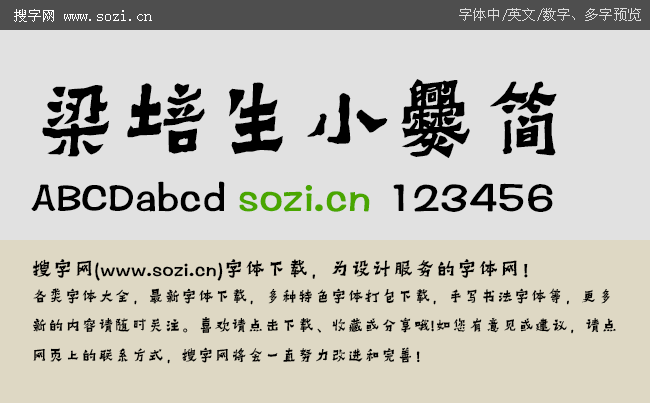
梁培生小爨簡
搜字網(wǎng)提供一款書法字體梁培生小爨簡下載,爨體字是1600年前魏晉時(shí)期,云南曲靖地區(qū)百姓為紀(jì)念爨氏家族給南中地區(qū)帶來的輝煌歷史所立碑文中的字體。爨體字介于隸書和楷書之間,端莊、古雅,適合商品包裝、牌匾店招、報(bào)頭題字、海報(bào)設(shè)計(jì)等廣告設(shè)計(jì)應(yīng)用。